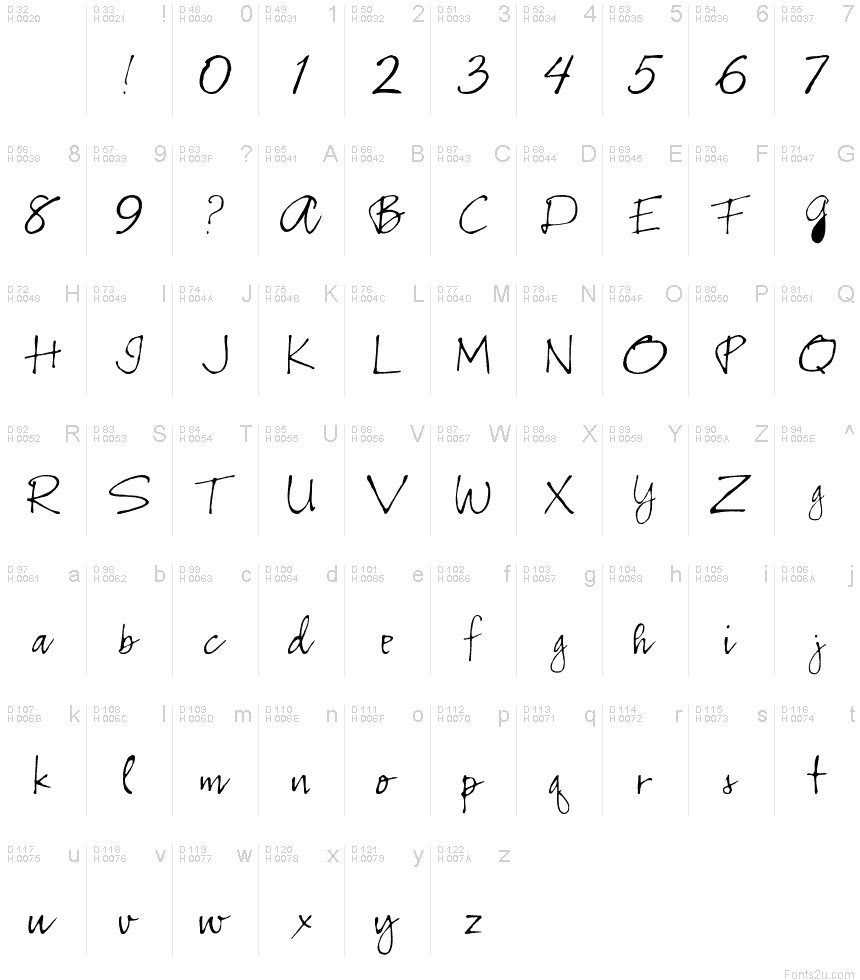
Riverside, un font manoscritto gratuito, ha il movimento sciolto tipico delle scritte dei cartellonisti. Le lettere si muovono con tratti ampi e densi, curve lunghe e ariose, e un ritmo leggermente irregolare che la rende dinamica, personale e un po' disinvolta, piuttosto che levigata.
Si adatta naturalmente a menu di caffè, titoli di cartoline, scrapbooking, packaging di boutique e loghi rilassati, dove un font gratuito con questo tipo di movimento fluido può definire l'atmosfera da solo. È perfetta per frasi brevi, specialmente quando cerchi una linea scritta a mano che risulti spontanea e leggermente teatrale, senza mai apparire rigida.
Riverside